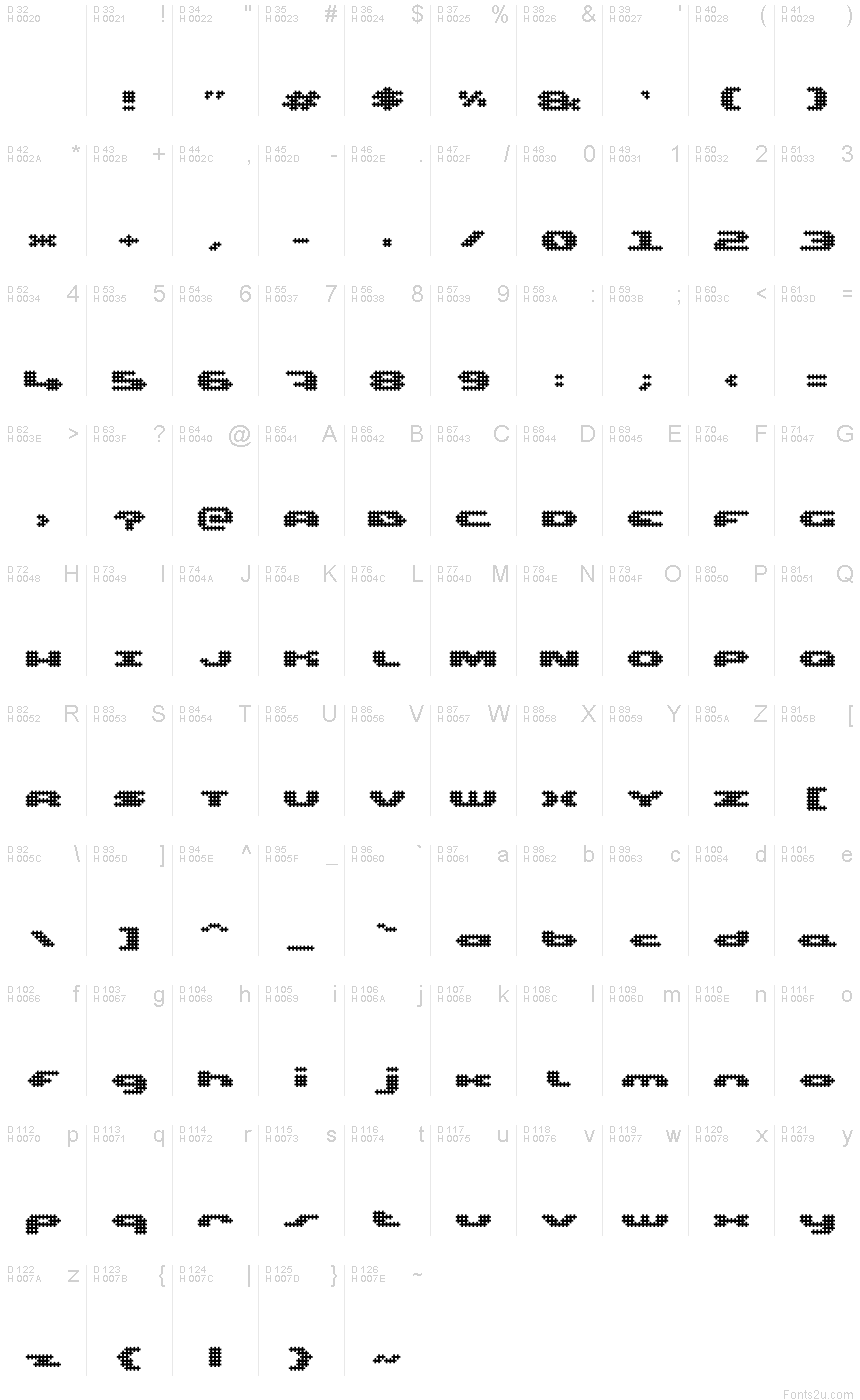
خط UP Tiny lcd four 8 decoC من UrbanPixel هو خط مجاني بنمط "بيت ماب" (Bitmap) وذو طابع LCD زخرفي مرح. الحروف مبنية من وحدات مربعة متراصة وخطوط عرضية قصيرة، مما يخلق إيقاعاً شبكياً قوياً يبدو رقمياً وزخرفياً بعض الشيء بدلاً من كونه نفعياً بحتاً.
يعمل الخط بشكل طبيعي في رسومات الألعاب القديمة (Retro)، وتسميات واجهات المستخدم، وعناوين الملصقات، وأغلفة المجلات المستقلة، وبطاقات العناوين، حيث تقوم تلك الملمس المربّع بفرض أسلوبها الخاص. كخط مجاني، فهو مناسب أيضاً للشعارات المدمجة أو الحروف المختصرة، لأن نمط الكتل المتكررة يمنح الكلمات القصيرة نبضاً إلكترونياً مميزاً.